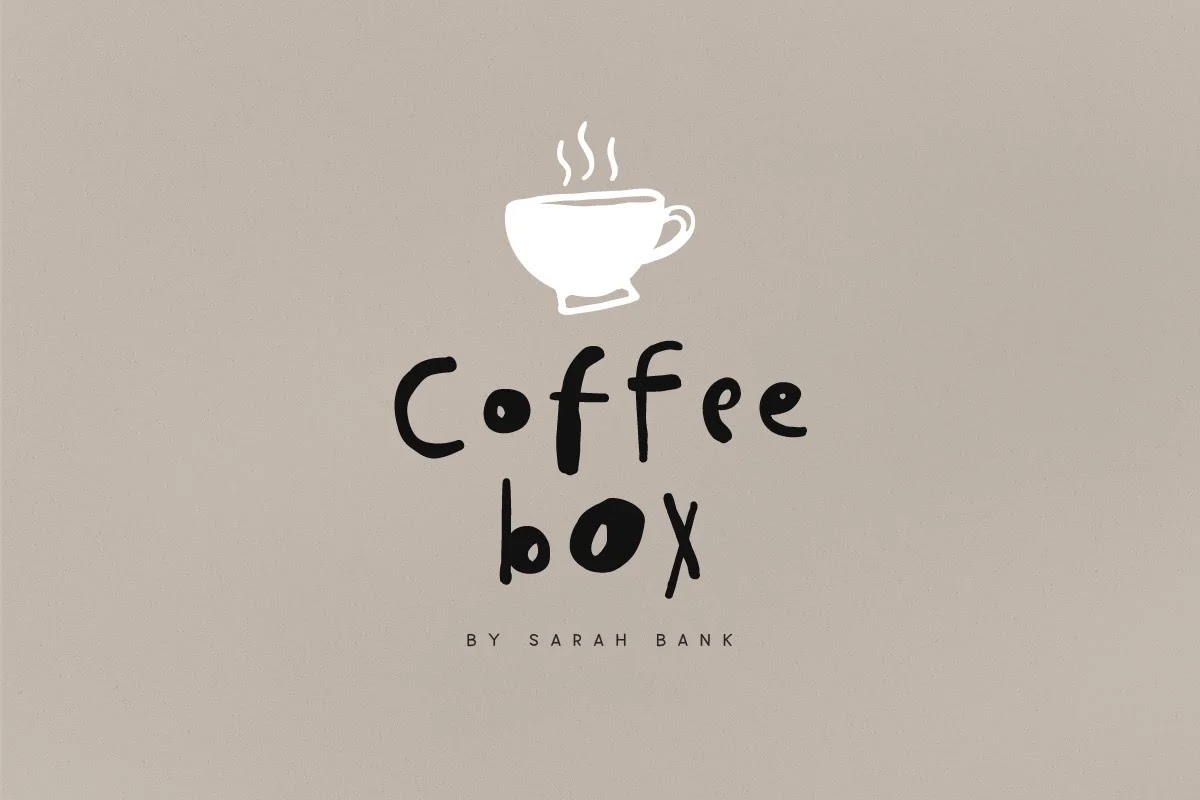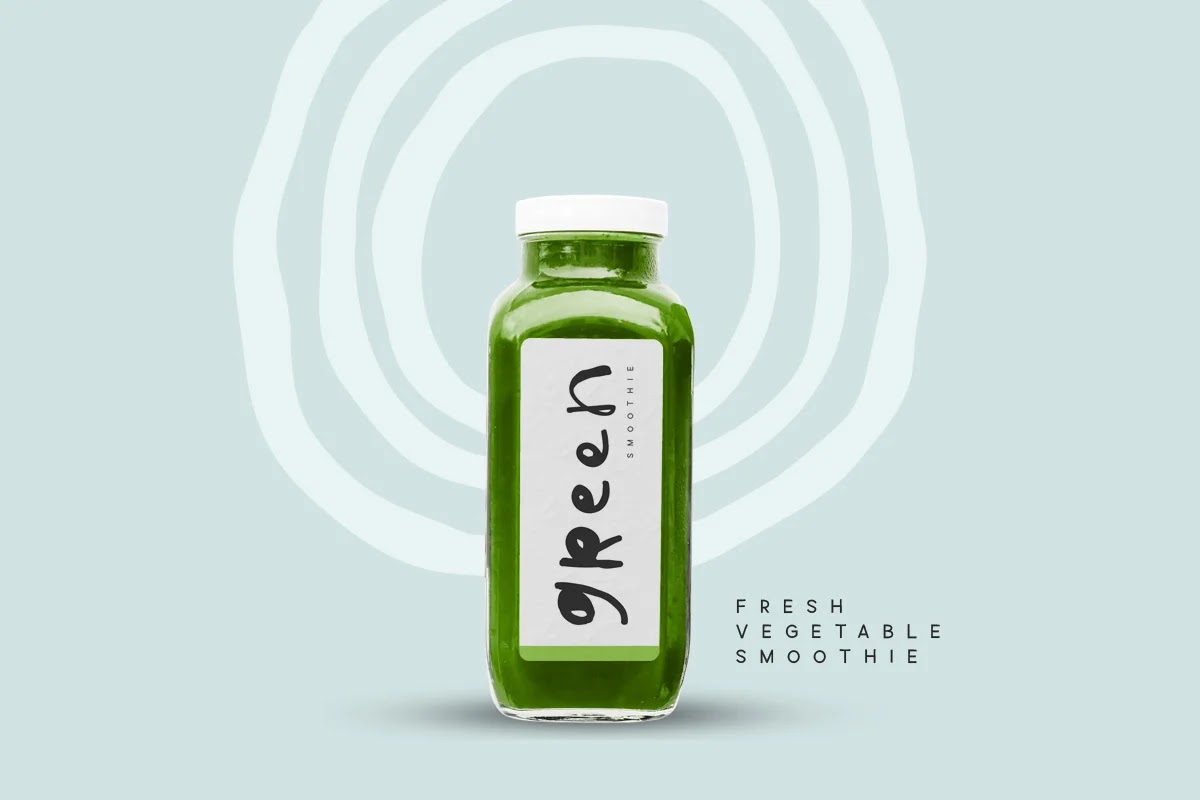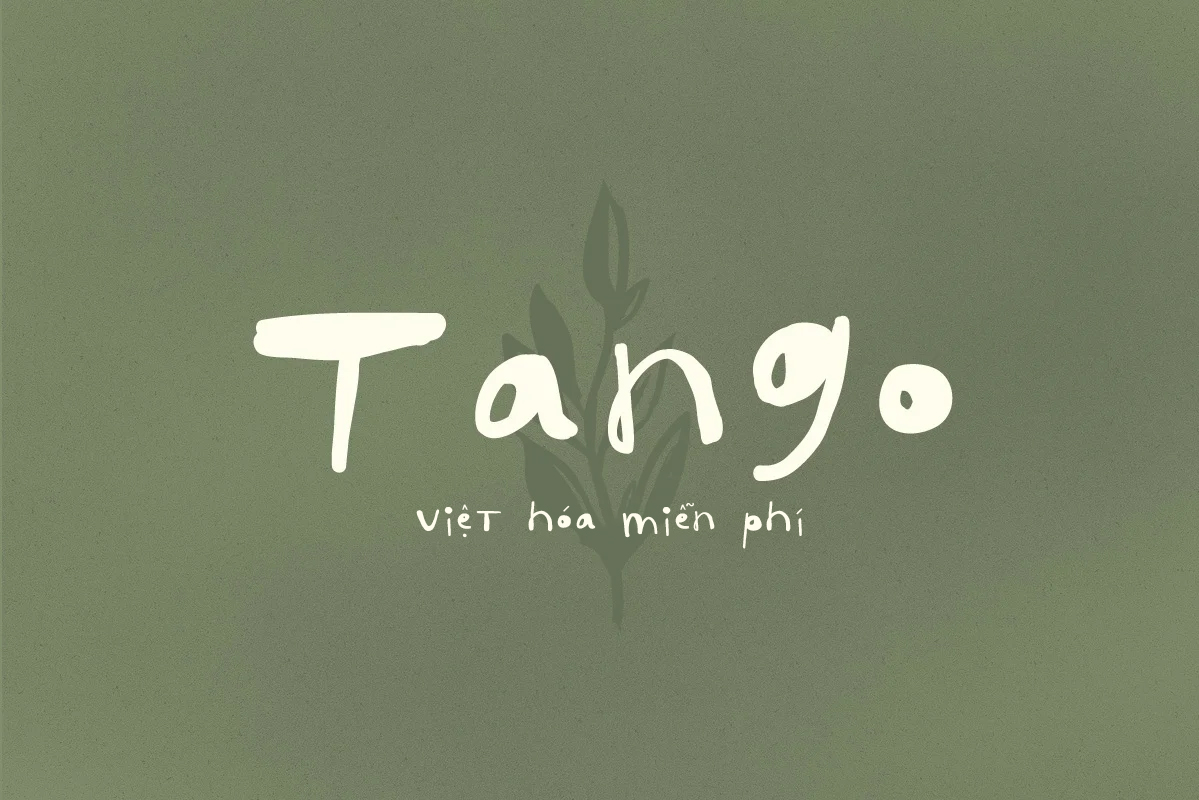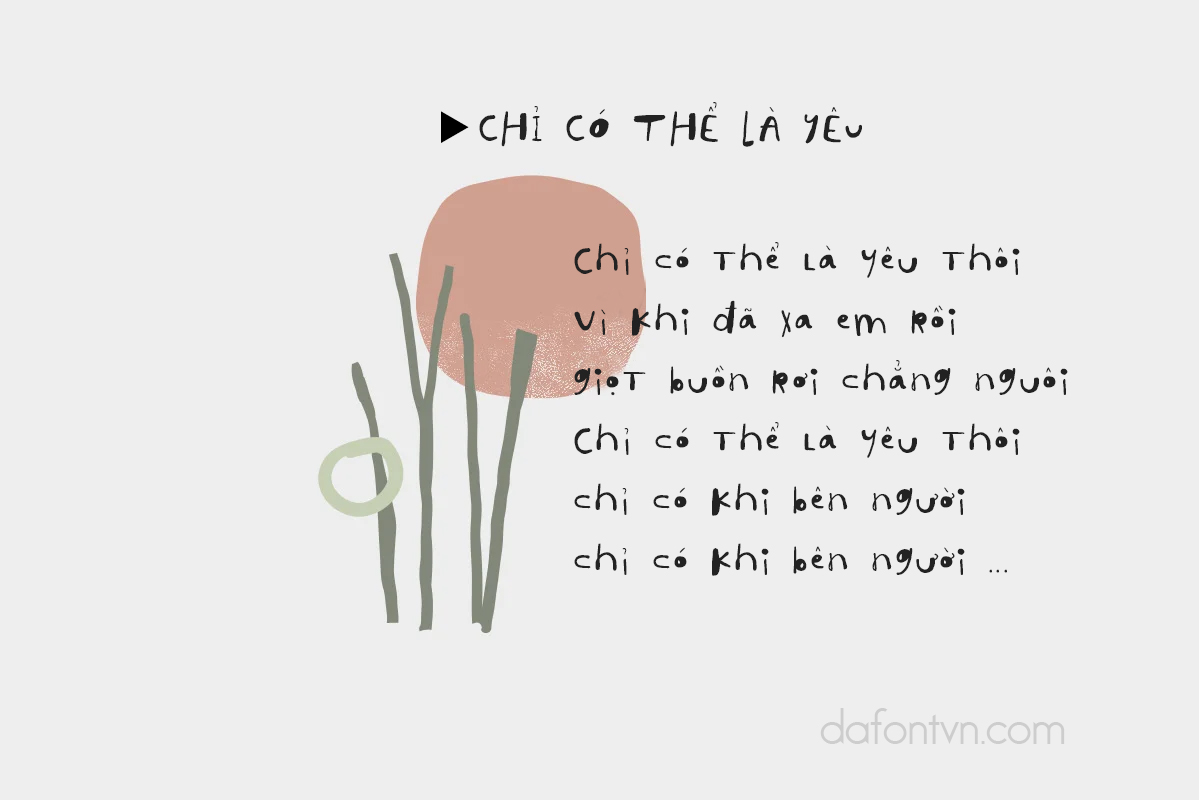
[Sans Serif] Download Font Tango Việt Hóa
Tango là font chữ vui nhộn hiện đại, mọi chữ cái đều được trau chuốt cẩn thận để làm cho văn bản của bạn trông đẹp mắt. Với phong cách vui nhộn hiện đại, font chữ này sẽ hoàn hảo cho nhiều dự án khác nhau, ví dụ: trích dẫn, tiêu đề blog, áp phích, đám cưới, thương hiệu, logo, thời trang, may mặc, thư, lời mời, văn phòng phẩm, v.v.
Font Tango Việt Hóa